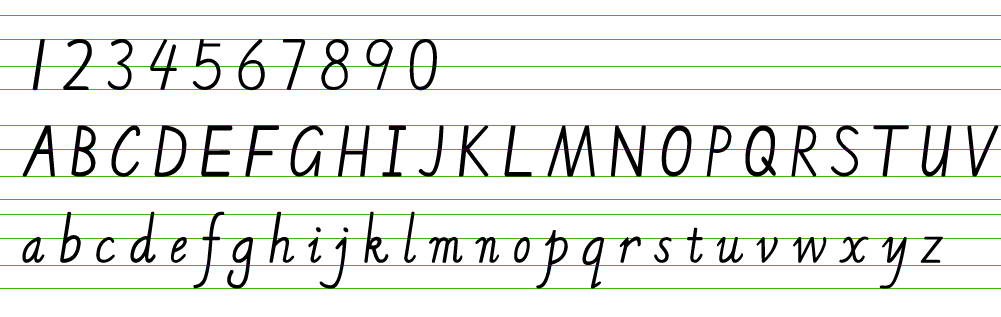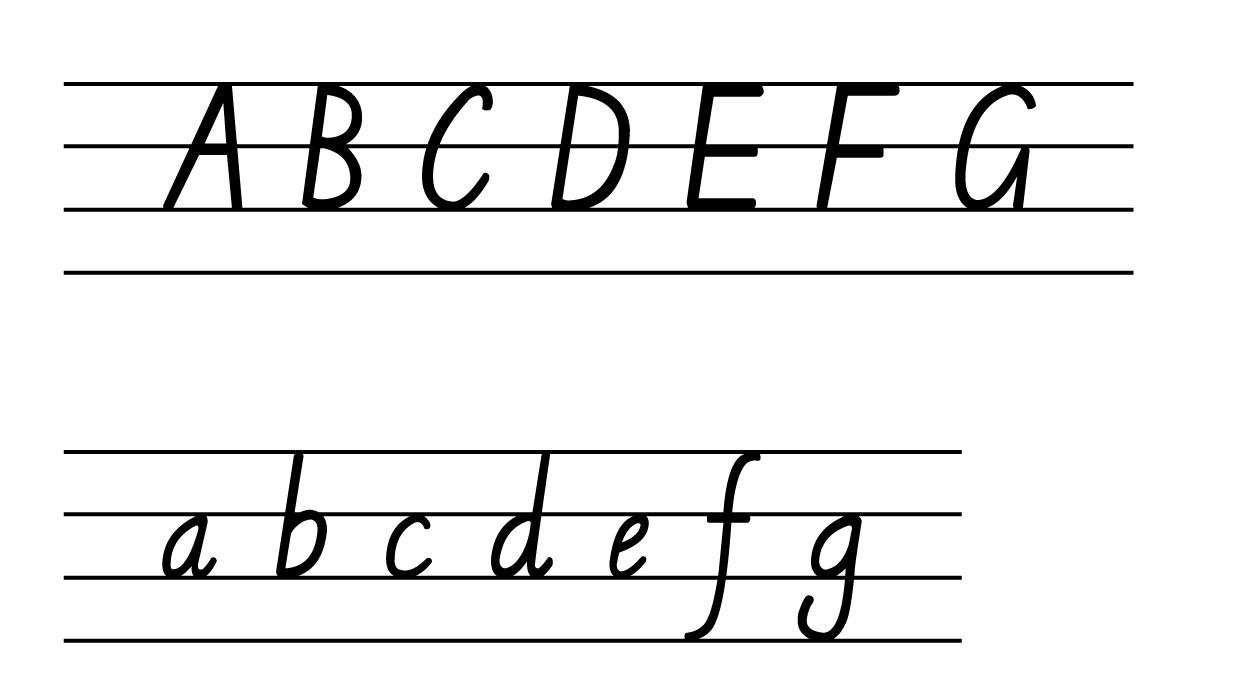
hengshuiti衡水体
hengshuiti衡水体,这款不带横线,绿色横线是ps里画的,下面有一款带横线的
这是一款带横线的
还有一款:SegoeUIItalic.woff.ttf 比较接近的衡水字体
衡水体和 Segoe UI Italic 的关系,及前者规范有哪些?
有的人把衡水体叫做手写印刷体,这我并不认同,因为手写体和印刷体是对立面关系,准确的说衡水体应该是无衬线意大利体。其中“衬线”是字体设计的用语,在书法的角度,应该叫“笔锋”。
进入正题,衡水体第一印象感觉就像 Segoe UI 的意大利体(也称真斜体),其中有不少相似之处。如字母在四线格中的占比等。但是也有许多问题,比如:
衡水体大写字母 I 应该是 Windows Vista ~ 7 的 Segoe UI,还是 Windows 8 ~ 10 的 Segoe UI 呢?也就是说 I 是否有上下两个小短横(也就是衬线)?
再如,衡水体大写字母 G 的右下角到底是 Segoe UI 的横折,还是某些网络上所见的衡水体的横,还是意大利斜体的竖?
此外还有更多的差异问题。
更重要的是,高考是否允许衡水体的存在,因为考纲所要求的标准字体是初中七年级上册英语书上的“意大利斜体”,如 G 的右下角必须写作竖等等,而与其背道而驰的衡水体究竟是否是高考所允许的?
还有倾斜的角度是与 Segoe UI Italic 一致的 10° 吗?
除此之外,与其搭配的中文字体是不是应该是微软雅黑或是其类似的字体?尽管英语考试不用写中文,日常生活中也不要求那样严格,但是本人实际上也研究一点字体,可以手写八种常见电脑印刷体,同时每个字体再搭配英文字体,再包括其意大利体与正体部分,一共 8×2×2=32 个字体,并且要求中英文字体搭配得当。所以此时应该手写微软雅黑斜体。目前在衡水中学的中文作文中发现的大多是隶书,感觉中英文字体搭配完全不协调。